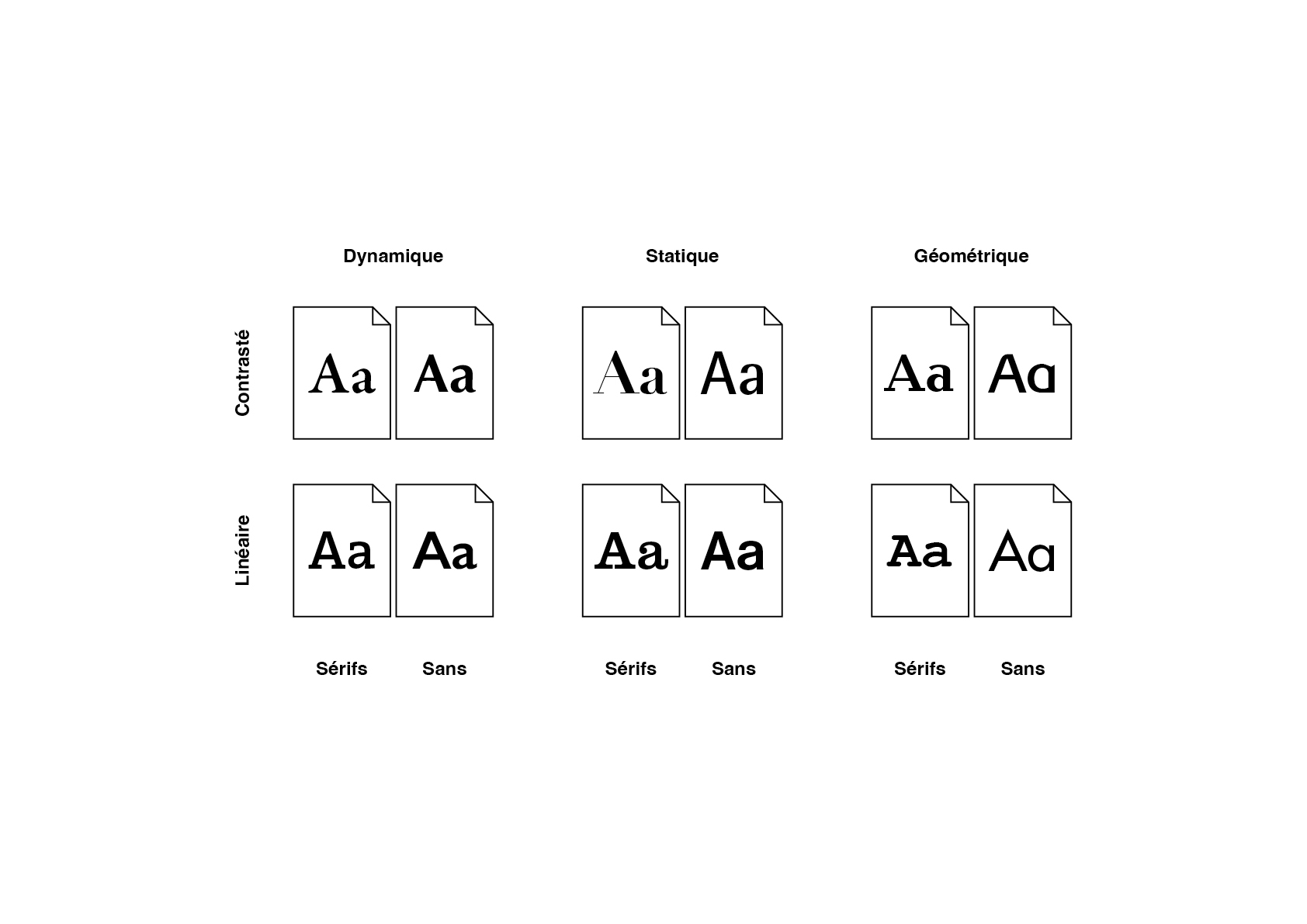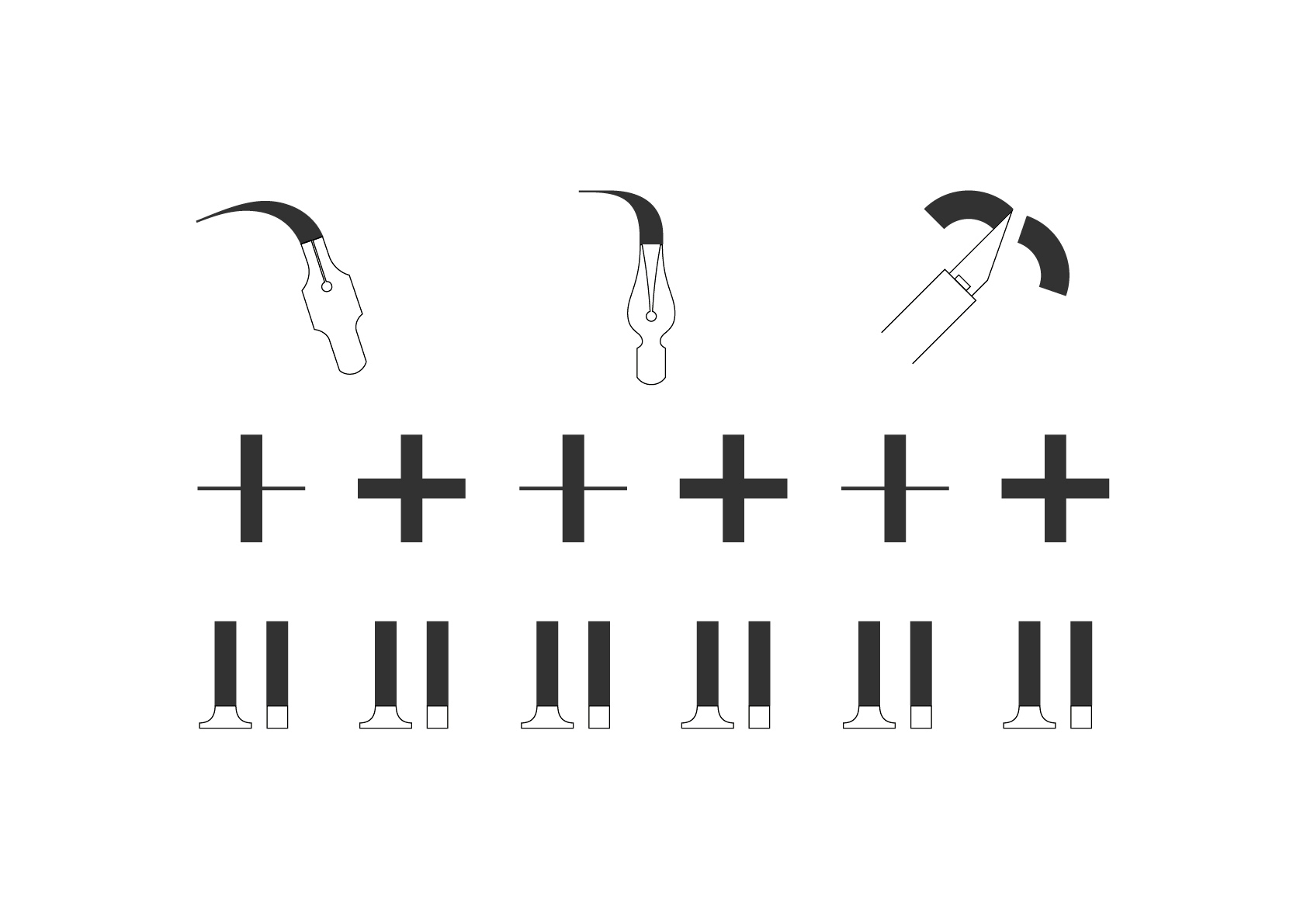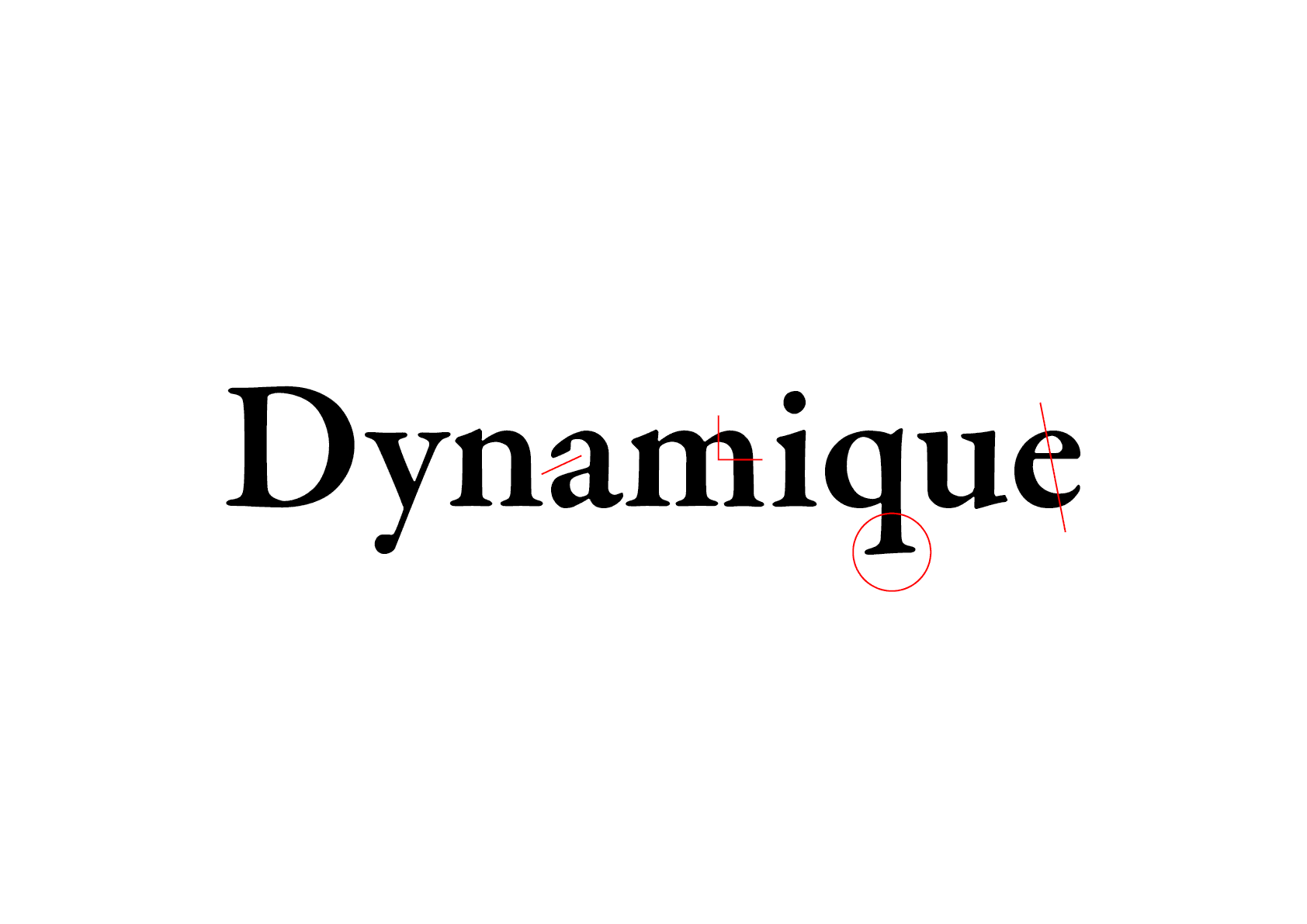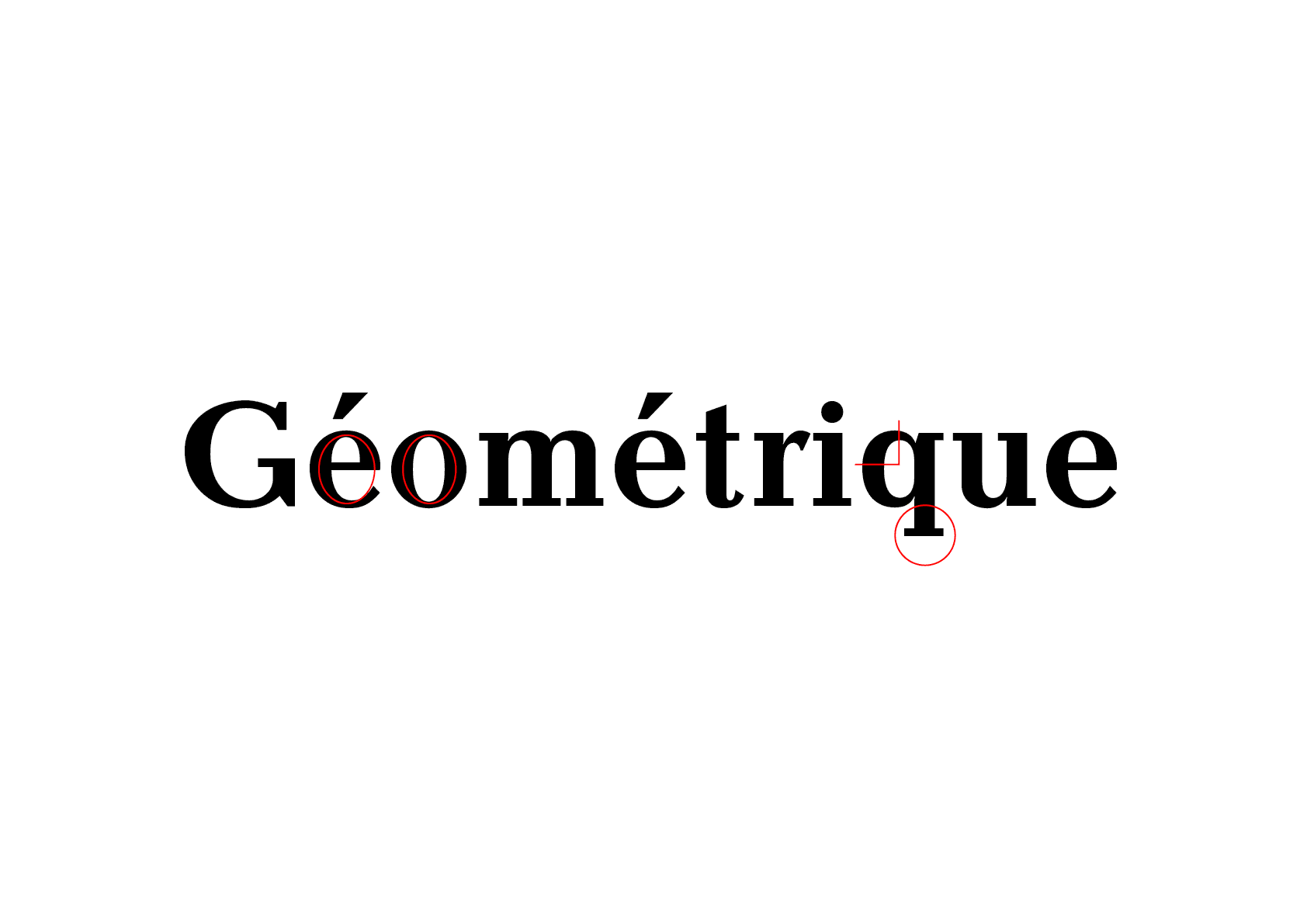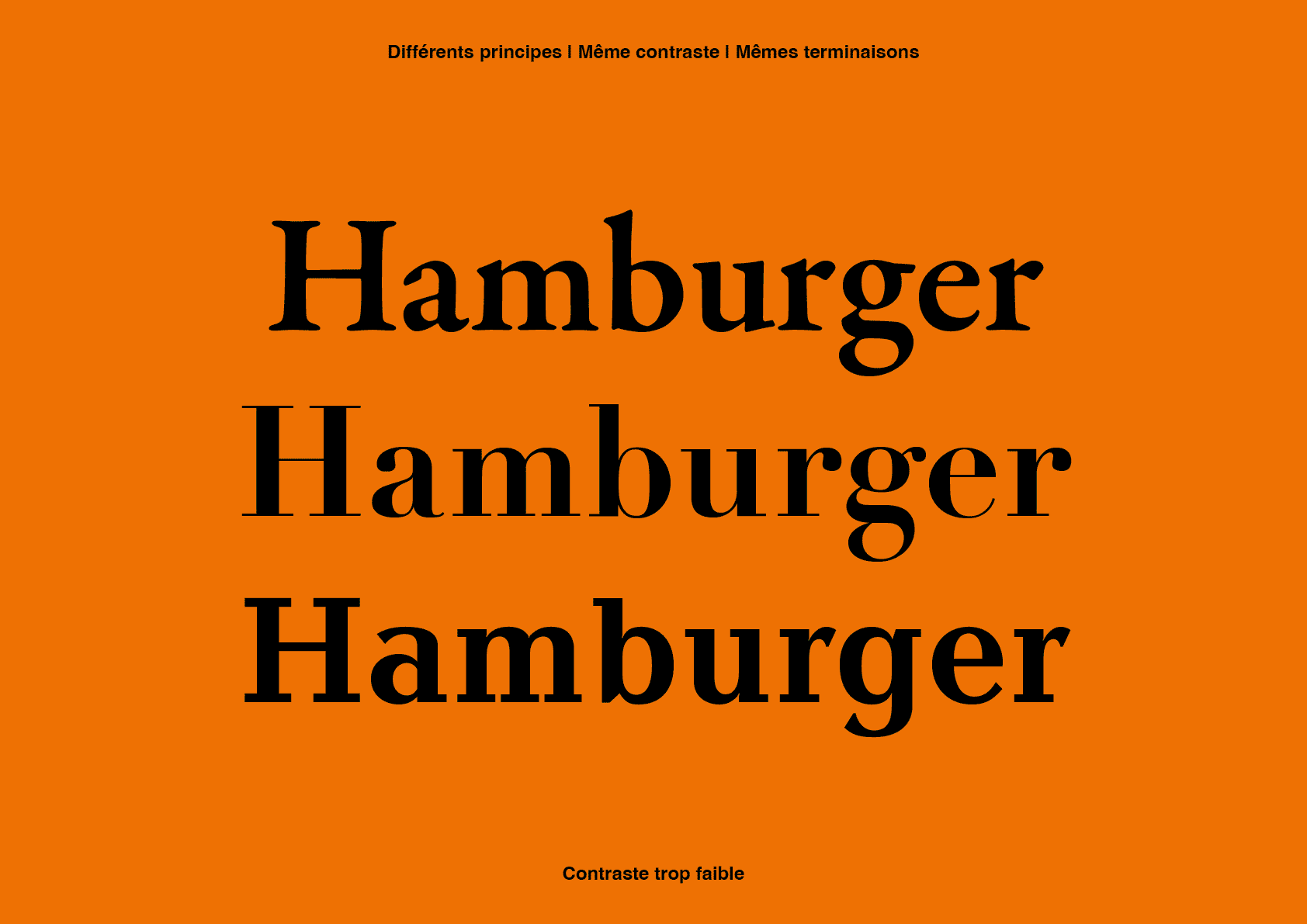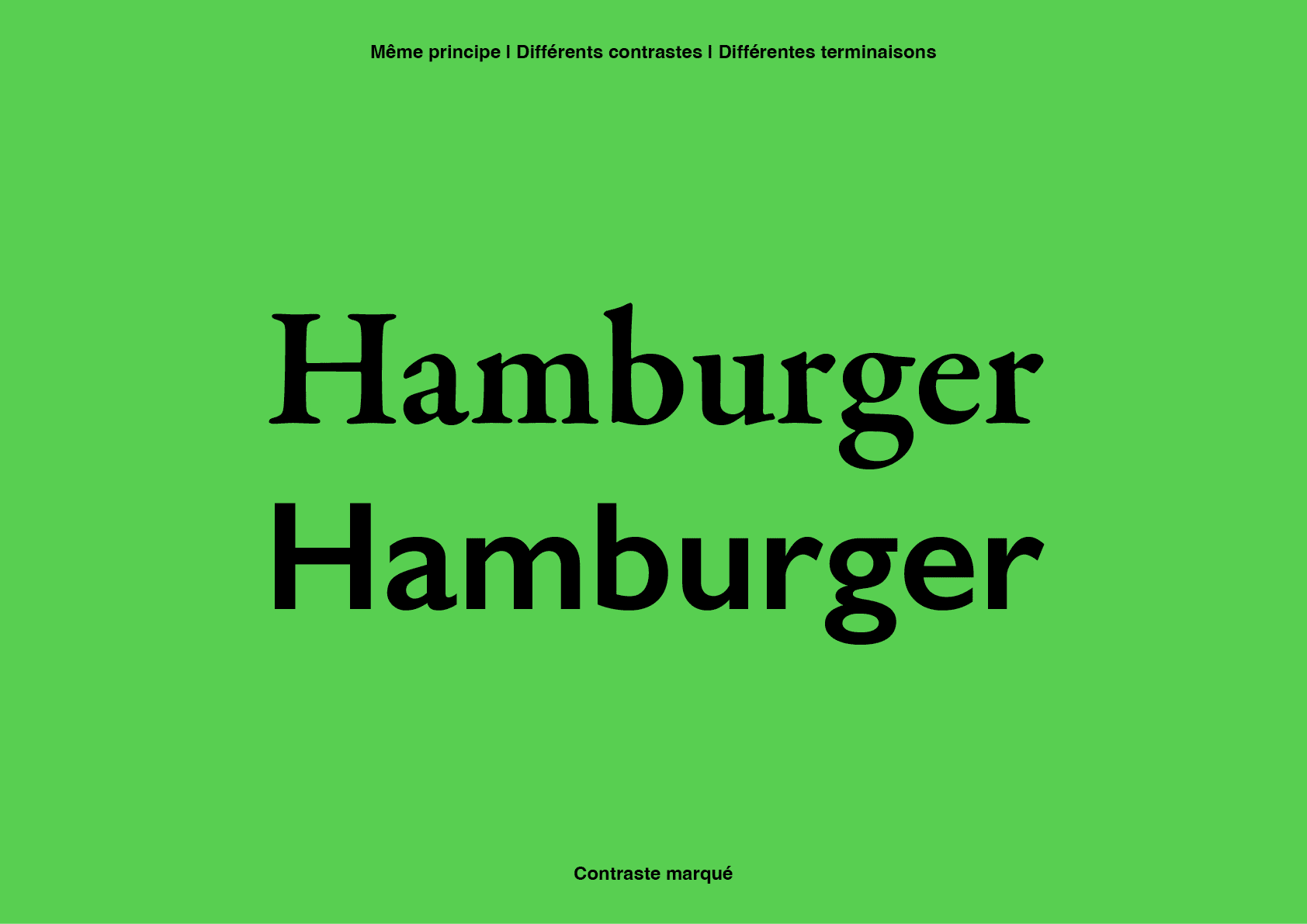
🦴 Classification Anatomique
Tableau
| Classification anatomique |
| Classification ramifiée basée sur l’anatomie des caractères |
Squelette - Graisse - Enveloppe
| Squelette - Graisse - Enveloppe |
Squelette
├── Dynamique
├── Statique
└── Géométrique
Graisse
├── Contrasté (avec)
└── Linéaire (sans)
Enveloppe
└── Terminaisons
├── Avec (sérifs)
└── Sans (sérifs)
├── Fûts
├── Ouvertures
└── Ornements
Squelette Dynamique
| Contrasté-Avec, Contrasté-Sans, Linéaire-Avec, Linéaire-Sans |
Vocabulaire sémiotique:
convivial, ouvert, accessible, flexible, naturel, démocratique, chaleureux, accueillant, personnel, intemporel
Squelette Statique
| Contrasté-Avec, Contrasté-Sans, Linéaire-Avec, Linéaire-Sans |
Vocabulaire sémiotique:
rationnel, ordonné, réservé, noble, élégant, sérieux, rigide, correct, rigoureux, autoritaire
Squelette Géométrique
| Contrasté-Avec, Contrasté-Sans, Linéaire-Avec, Linéaire-Sans |
Vocabulaire sémiotique:
géométrique, simple, technique, moderne, fonctionnel, informel, systématique, sobre, construit, épuré
Combinaisons
| Combiner des fontes avec la classification formelle[^3] |
En se basant sur la classification formelle de Indra Kupferschmid, on peut faire les remarques suivantes concernant les combinaisons:
- Les fontes du même modèle s’accordent bien
- Les fontes de modèles différents qui partagent le même contraste et les mêmes terminaisons ne s’accordent pas bien
- Les fontes de modèles différents s’accordent bien seulement si elles sont éloignées dans le tableau (plus qu’une colonne d’écart)
Ce système est un point de départ, il n’y a pas de règles absolues en matière de design. Il est nécesaire d’affiner les combinaisons en prenant en compte le contexte de votre projet, notamment les points suivants:
- la concordance des proportions (hauteur de x, hauteur des capitales)
- les hiérarchies
- les corps
- les graisses
- les styles
- les character-sets
- etc.
| Différents principes | Même principe |
| Même principe | Différents contrastes & terminaisons |
| Différents principes | Différents contrastes & terminaisons |